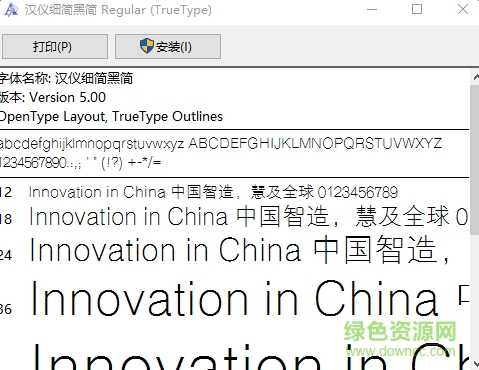
漢儀細(xì)簡(jiǎn)黑簡(jiǎn)字體是漢儀字庫(kù)中很實(shí)用的一款簡(jiǎn)體字體,這款字體寫出來(lái)的字是很好看的,規(guī)范整齊,而且可以用于很多方面,歡迎有需要的朋友來(lái)綠色資源網(wǎng)下載。
漢儀細(xì)簡(jiǎn)黑簡(jiǎn)字體是一款很不錯(cuò)的電腦字體,可以用于書(shū)本印刷、廣告設(shè)計(jì)等方面,喜歡的朋友可以來(lái)綠色資源網(wǎng)下載。